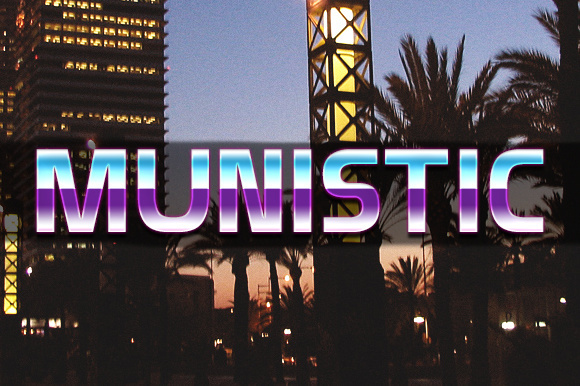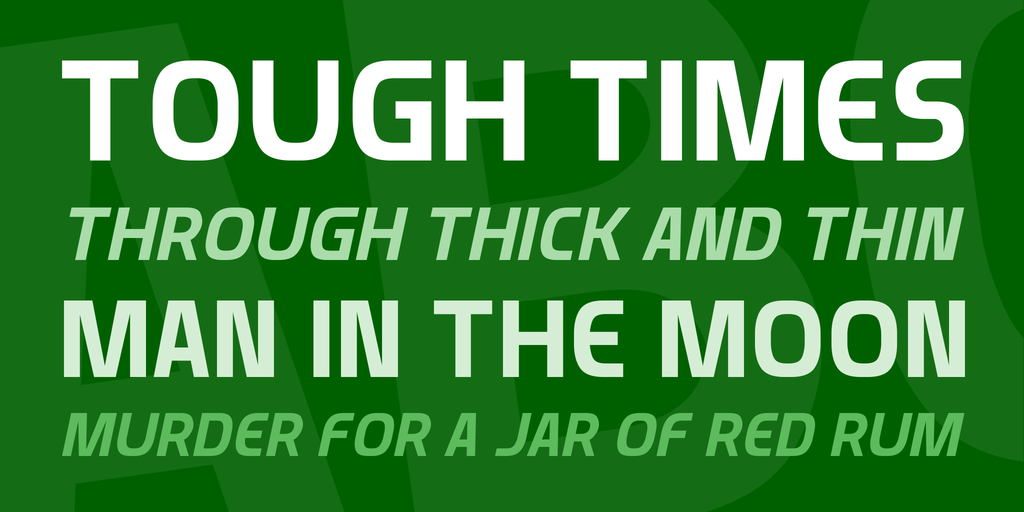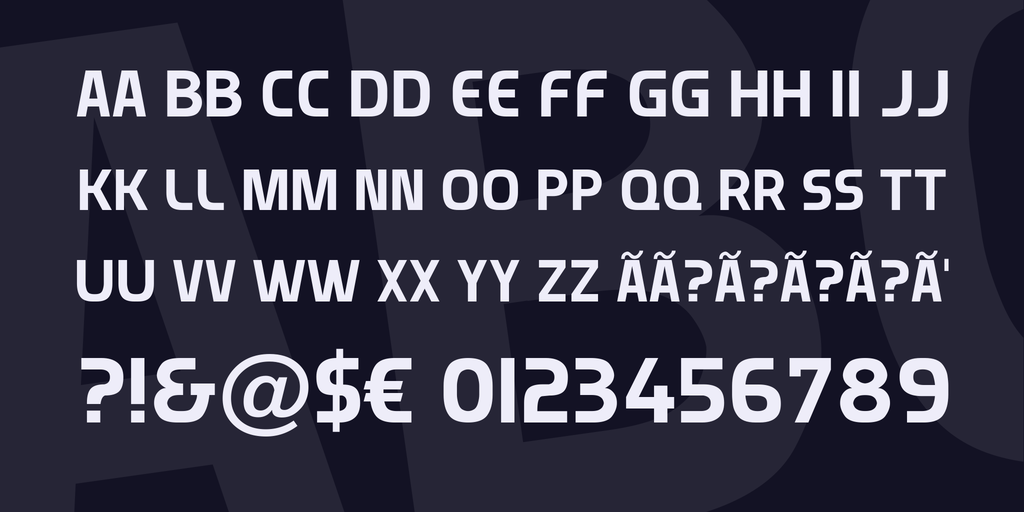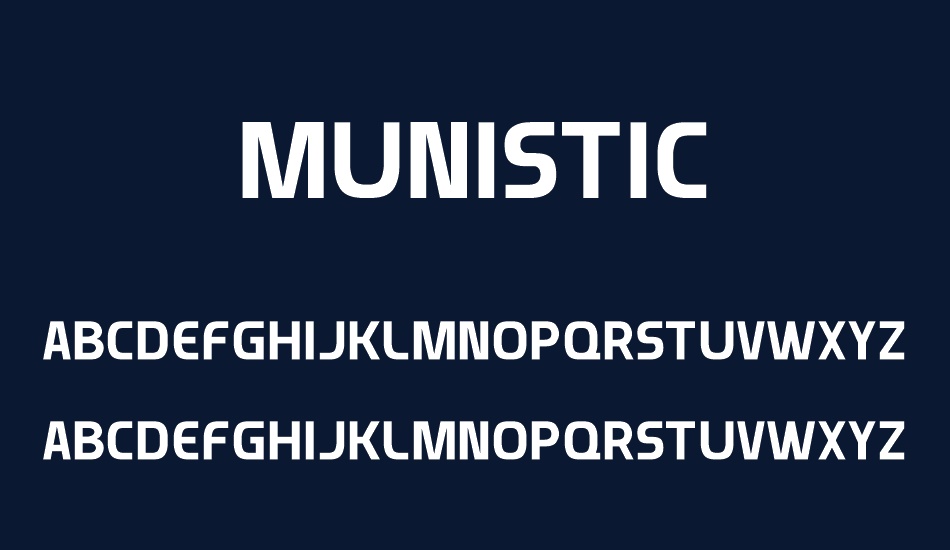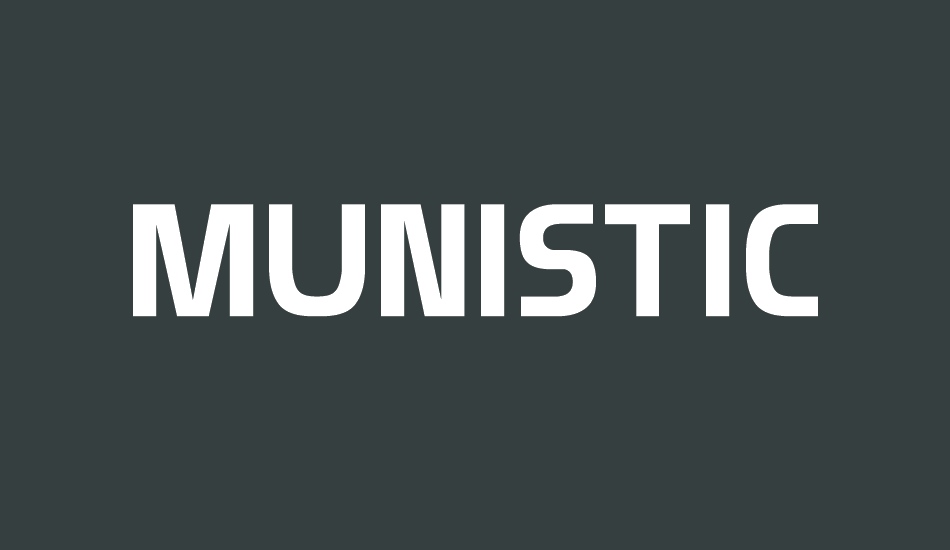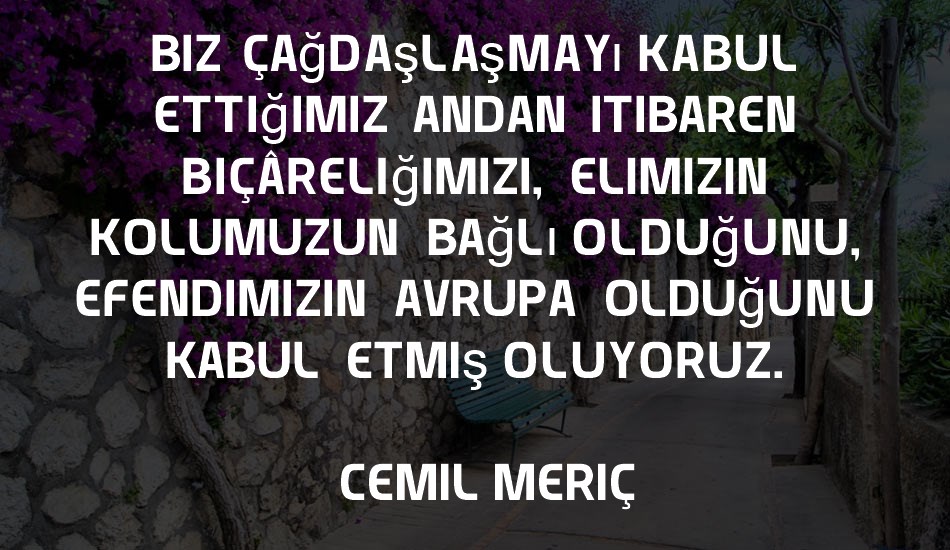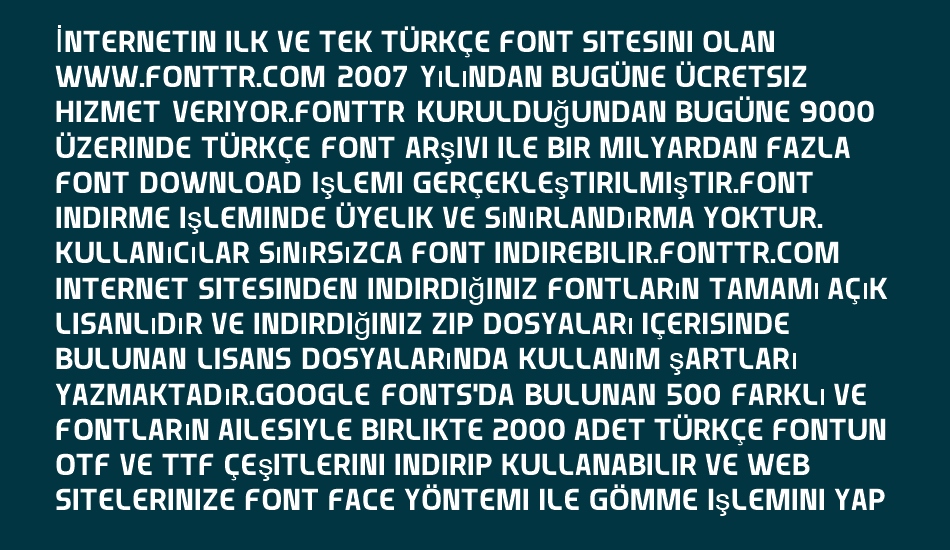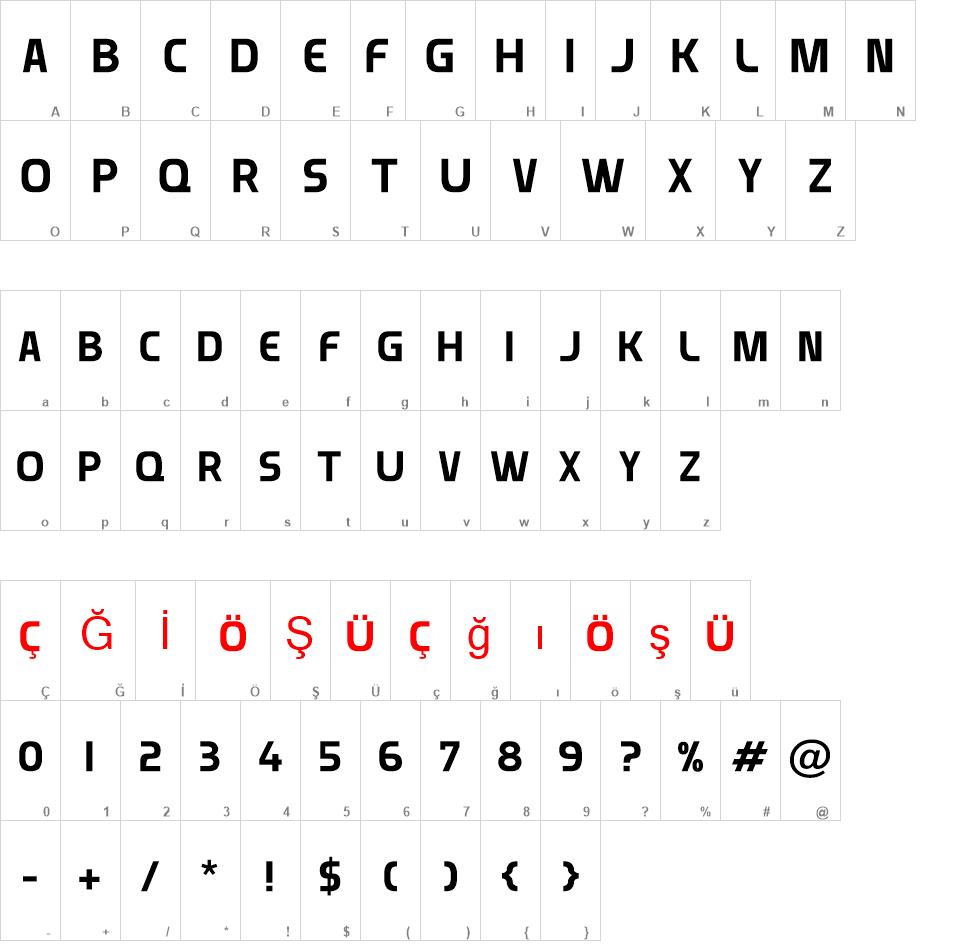
Munistic Font
Munistic ist eine Retro-Futurismus-Schrift mit einem modernen Stil. Mit seinen auffälligen Buchstaben in zwei Stilen ist Munistic ideal für jedes Design, das herausstechen muss.
Munistic font